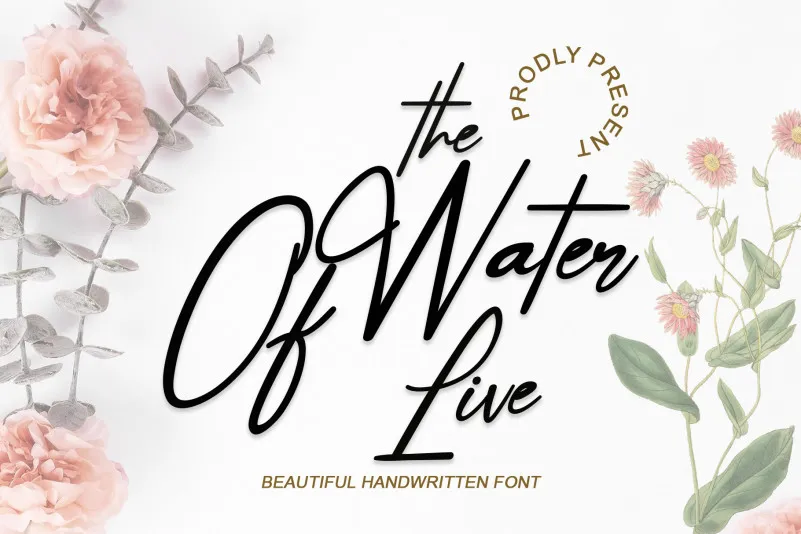
The Water Of Life Font – Fonte Grátis
The Water Of Life Font
Esta é uma elegante e fluida fonte escrita à mão. Ela mantém seus influentes traços chamuscados ao mesmo tempo contemporânea e alegre. Uma vez que cai no amor com esta fonte, você irá levantar os projetos para um nível superior. O designer kateengciu criou uma fonte escrita à mão de alta qualidade, que transmite sutileza e delicadeza. Seja para aplicativos pessoais ou profissionais, ela certamente dará um toque único aos seus documentos. Esta fonte é perfeita para aqueles buscando algo que combine elegância com modernidade leve na sua próxima criação visual. Não deixe de experimentar The Water Of Life Font e veja como ela pode adicionar profundidade à sua produção visual.